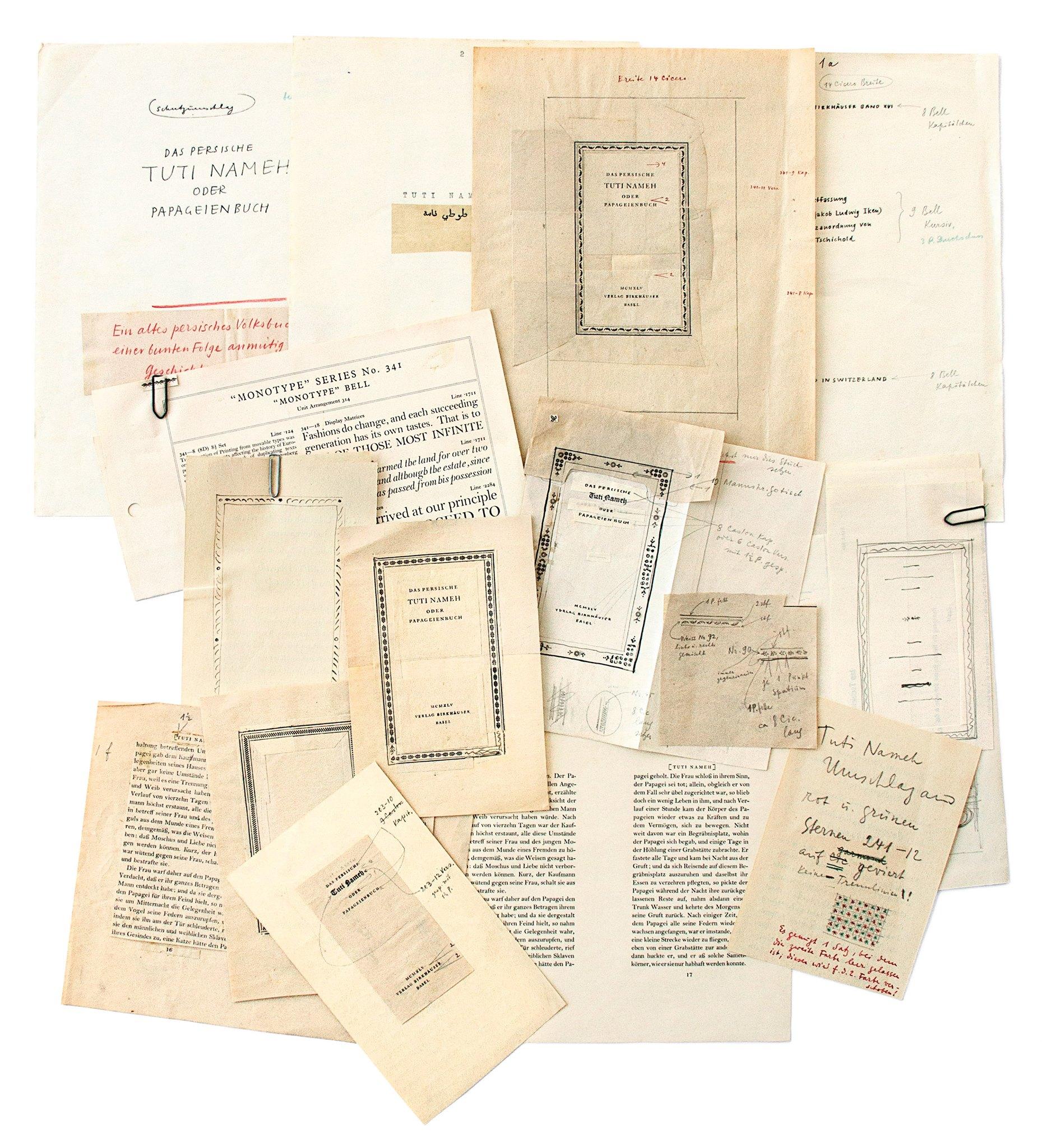
Der Leipziger Typograf Jan Tschichold und seine Arbeitsbibliothek. Ausstellung vom 5. März bis 14. Mai 2017 im Museum für Druckkunst Leipzig.
Jan Tschichold wurde 1902 in Leipzig geboren und besuchte die Akademie für graphische Künste und Buchgewerbe, heute HGB. Sein Name ist unter Verlegern, Buchhändlern, Bibliothekaren, Bibliophilen, Typografen und Buchgestaltern weltweit bekannt. Seit frühester Zeit und bis zu seinem Tod 1974 in der Schweiz hat er unablässig publiziert. Mit seinen Arbeiten, seinen Büchern und einer Unzahl von Artikeln hat er die Typografie der westlichen Welt im 20. Jahrhundert entscheidend geprägt. 2010 haben die Erben von Jan Tschichold der Kantonsbibliothek Vadiana in St. Gallen dessen Arbeitsbibliothek geschenkt, ein wahrer Schatz an Zeugnissen zur Geschichte der Typografie.
Die Ausstellung bietet in 24 Vitrinen einen Querschnitt durch diese Arbeitsbibliothek und zeigt Dokumente, die neues Licht auf Persönlichkeit und Werk von Jan Tschichold werfen.